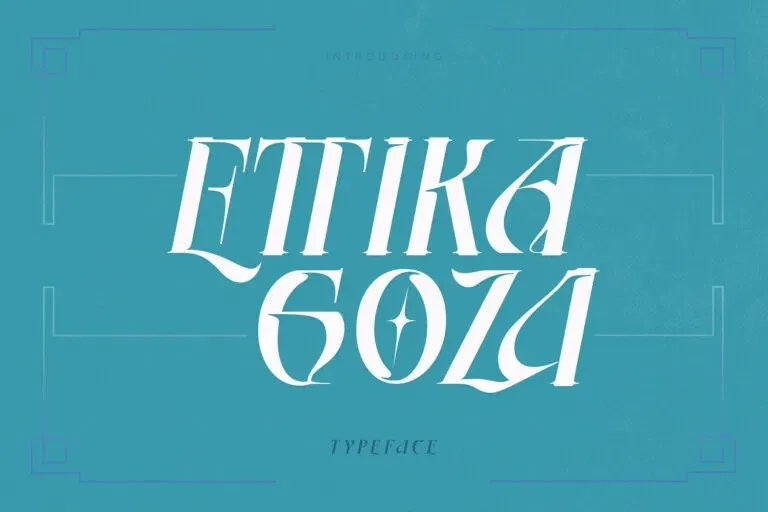
A fonte Ettika Goza é uma elegante tipografia serifizada criada pelo designer alit design. Com seus estilos alternativos e únicos, esta fonte de display oferece um estilo elegante e inclinação robusta que dá ao seu design singularidade e originalidade. Ideal para trabalhos com temas clássicos, designs retro e posters, Ettika Goza é uma escolha perfeita para designers procurando dar um toque único a suas criações. Não apenas complementará sua identidade visual de maneira única, mas também ajudará a tornar seus projetos memoráveis e diferenciados. Seja você um designer gráfico ou editor de imagens, não hesite em experimentá-la; ela certamente brilhará em seus trabalhos.